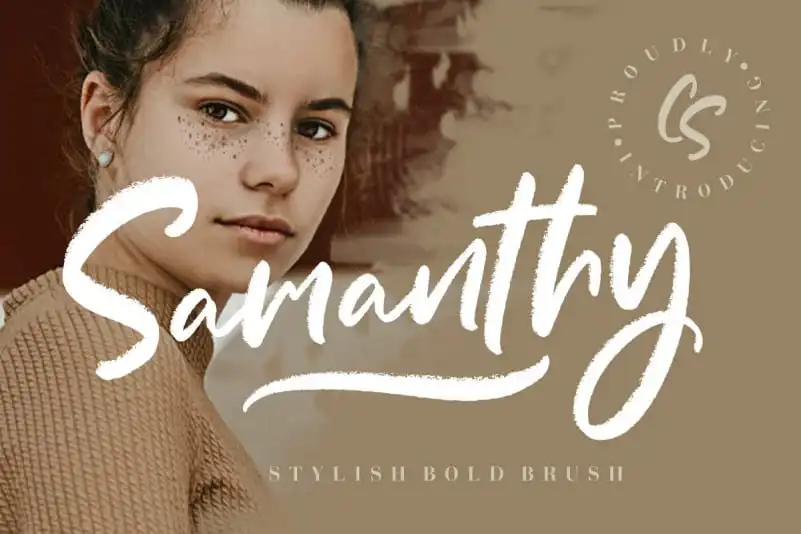
Samanthy Stylish Brush Font – Fonte Grátis
Samanthy Stylish Brush Font
A Samantha Stylish Brush Font surge diretamente do autógrafo humanoide, com uma fusão sofisticada entre curvas atraentes e vibes retro, criando um estilo script de mão-pintura que irá destacar qualquer projeto. Esta fonte é perfeita para aplicação em branding, logotipos, designs de casamentos, posts no social media, anúncios, embalagens de produtos, design de produto, rótulos, fotografia e até mesmo ícones de água-marinha e material de convite. A Samantha Stylish Brush Font adicionará um toque único ao seu trabalho e tornará-o mais atraente para qualquer projeto que precise de uma pitada de arte da escrita manual. Seja para criar uma identidade visual, adicionar personalidade à sua marca ou ilustrar seus designs com um ar nostálgico dos anos 80 e 90, esta fonte é o seu companheiro ideal.